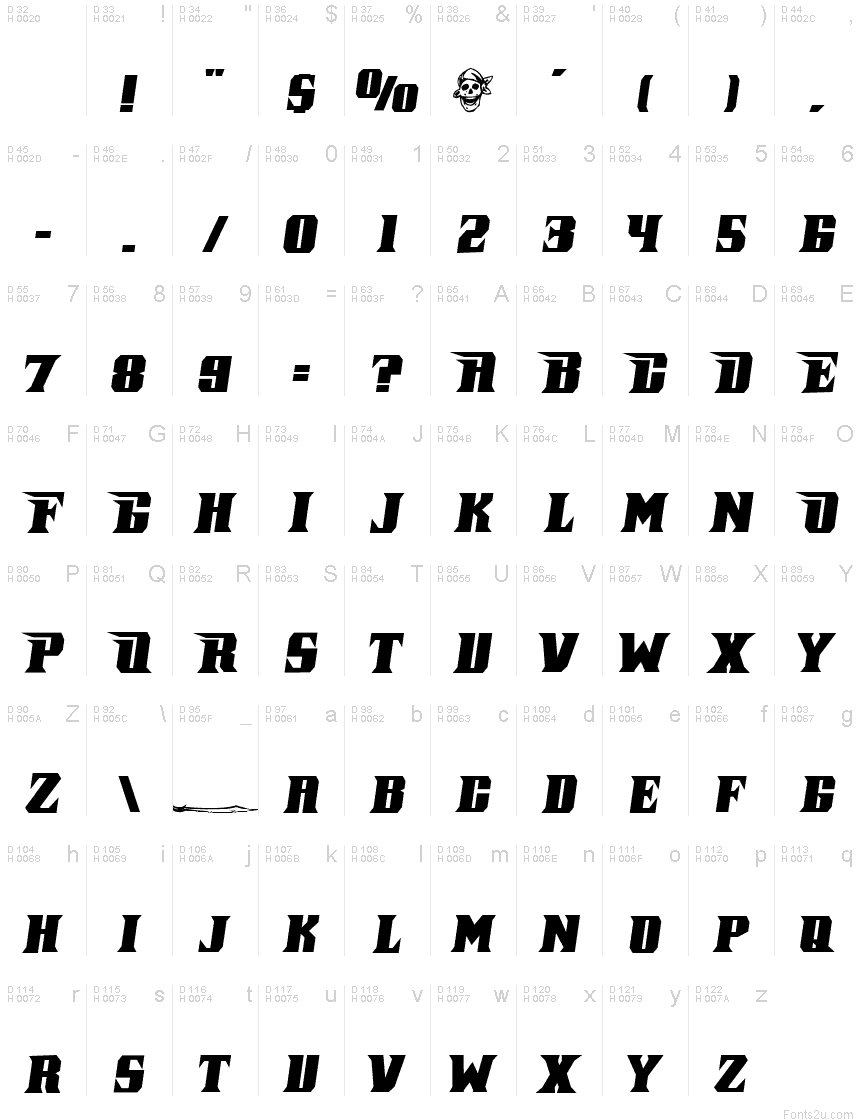
Pirate Keg Italic, stworzony przez Sharkshock Productions, to darmowy techniczny font wyświetlaczowy (display) w wersji samych wielkich liter, wyróżniający się ostrym, gamingowym charakterem. Litery zbudowane są z masywnych, kanciastych bloków, ciętych wyrazistymi skosami i wąskimi nacięciami. Nadaje to alfabetowi energiczny, pancerny rytm, który bardziej kojarzy się z estetyką automatów arcade i emblematami science-fiction niż ze zwykłym krojem pisma.
Font ten naturalnie wpisuje się w nagłówki plakatów, grafikę e-sportową, okładki albumów, plansze tytułowe i gadżety, wszędzie tam, gdzie krótkie słowa wymagają industrialnego, „wyciosanego” uderzenia. Jako darmowe narzędzie, świetnie sprawdzi się również w logotypach, monogramach i na opakowaniach, szczególnie gdy zależy Ci na tym, aby wielkie litery wyglądały kompaktowo, mechanicznie i bojowo.